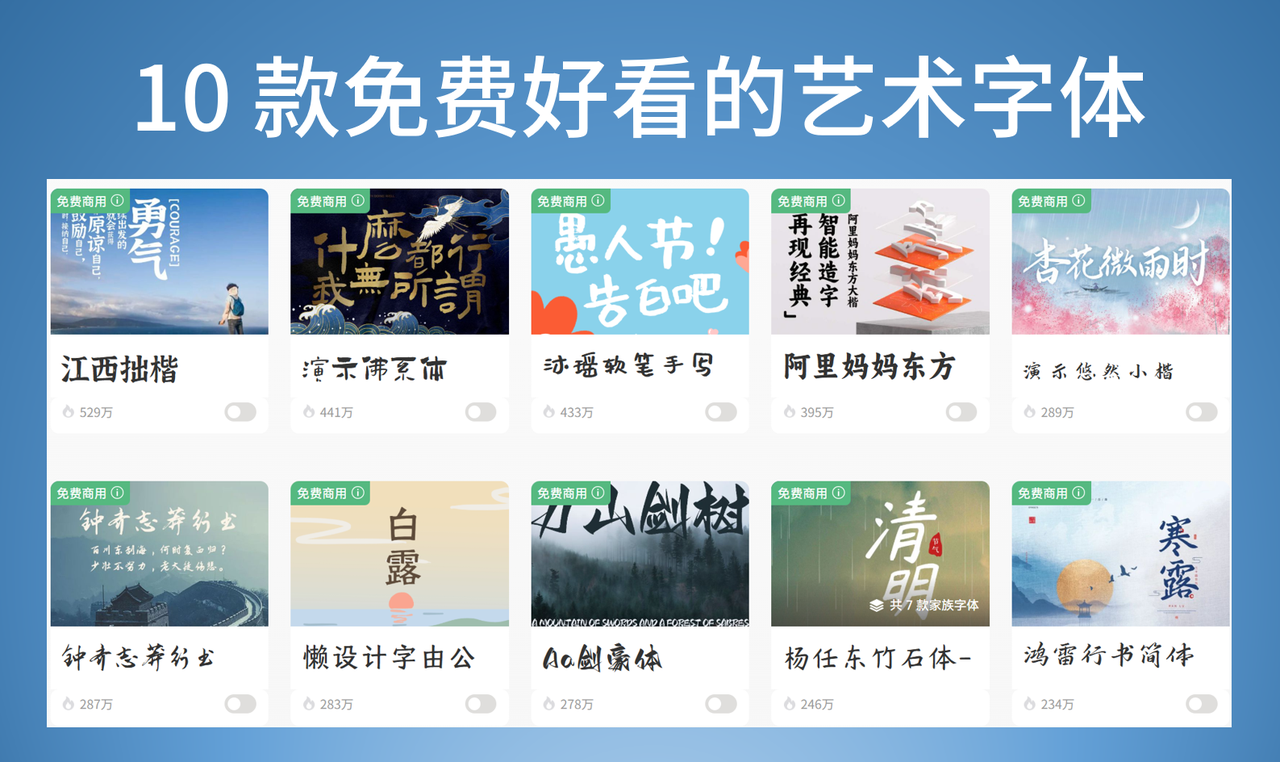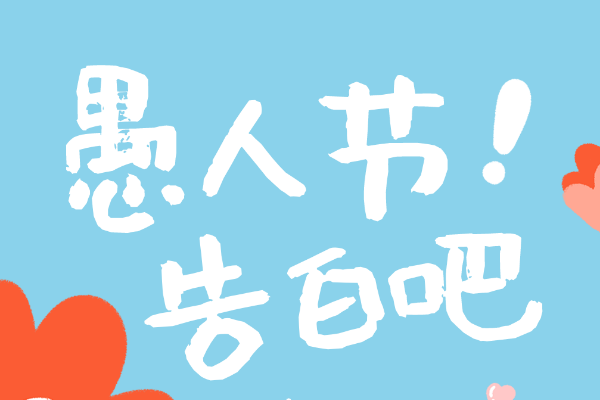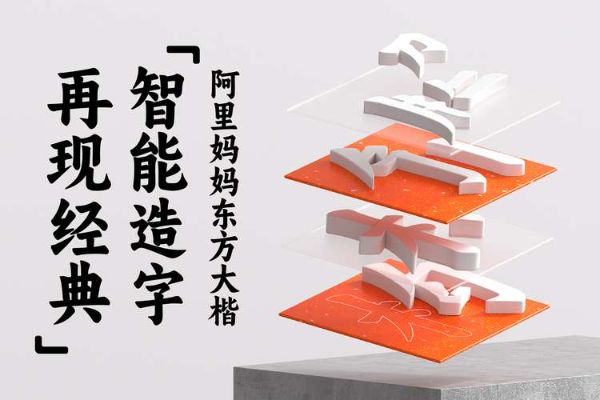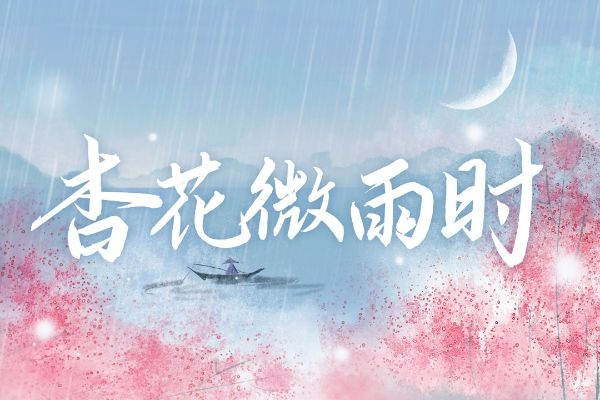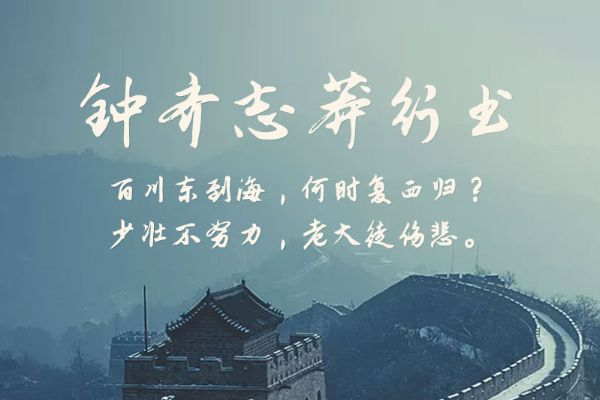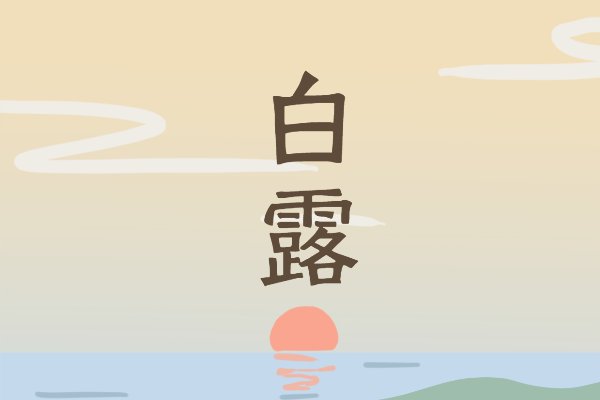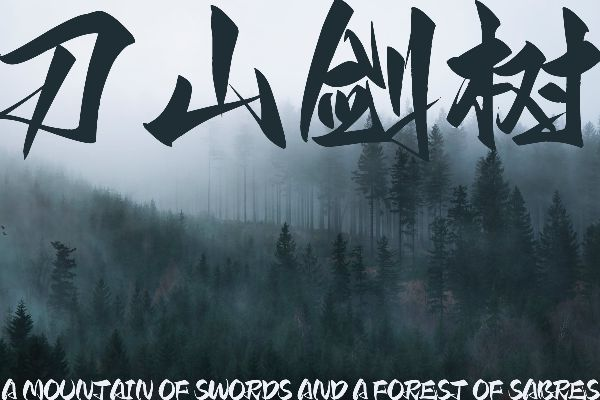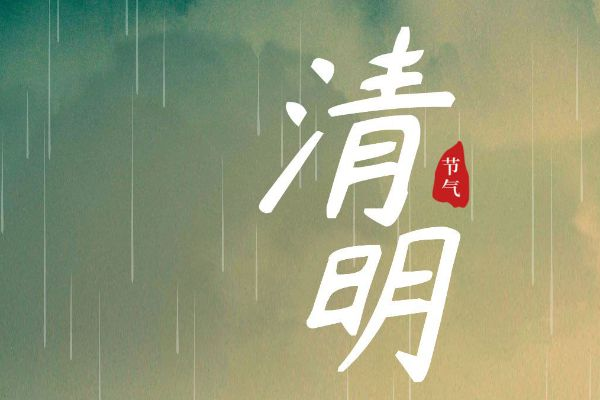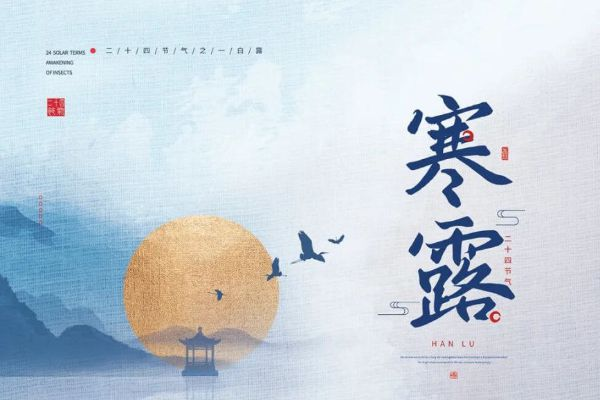
艺术字体大全,10 款免费好看的艺术字体分享
艺术字体是设计师和文案工作者们常用的一种字体类型。无论是海报设计、品牌LOGO,还是各种创意排版,艺术字体总能带来独特的视觉冲击力。本文会重点给大家分享 10 款免费好看的艺术字体,帮助大家在设计海报和其它作品时,更加有艺术感。
一、什么样的字体才算艺术字体
艺术字体不仅仅注重字形的清晰传达,更关注字体的视觉美感和表现力的字体。它们往往具有较强的个性化和装饰性,可以通过曲线、笔触、色彩甚至三维效果来表达独特的艺术风格。艺术字体不像常规的宋体、黑体那样严谨规范,而是更自由、更具创造性,适合用来表达情感和氛围。
二、艺术字体的特点
1. 个性鲜明
艺术字体形态多样,可能是优雅的曲线,也可能是粗犷的笔触,甚至结合了多种设计元素。所以具有强烈的个性特点,能够迅速吸引观众的注意力。
1. 装饰性强
相比标准字体,艺术字体更注重视觉装饰效果,往往带有复杂的线条、阴影、渐变和花纹,使字体本身成为一种艺术品。
1. 灵活多变
艺术字体的设计非常灵活,可以根据不同的主题和情境进行调整和创新,满足不同的设计需求。
1. 易于传递情感
艺术字体通过形态和设计传达特定的情绪和氛围,比如浪漫、复古、现代、街头风等,增强视觉沟通的效果。
三、艺术字体的使用场景
1. 品牌标识设计
作为品牌的标识,当然需要更具有艺术感,更容易被用户记住,例如时尚品牌、餐饮品牌常用手写风格或复古风艺术字体,增强辨识度。
1. 海报
尤其在影视宣传海报中,艺术字体非常受欢迎,尤其是电影海报、演唱会宣传等,需要强烈视觉冲击和情感表达的场合。
1. 书籍封面与杂志排版
为了吸引读者注意,书籍或杂志封面常用艺术字体来突出主题,增强视觉美感。
1. 网页设计和社交媒体
在网页标题、Banner和社交媒体配图中,艺术字体可以提升整体设计感,吸引更多点击和关注。
1. 包装设计
食品、化妆品等产品包装中,艺术字体能够传达产品的独特风格和品质感。
四、10 款免费好看的艺术字体
1. 江西拙楷
江西拙楷是一款充满传统韵味的楷书字体,这款字体在设计上强调笔画的厚重感和结构的严谨性,让人感受到中华汉字的独特魅力。
字体特点:
• 字体的笔画粗细适中,书写感厚实,笔力遒劲,给人一种稳重坚实的感觉。
• 字形布局方正,结构平衡,每个字的重心都非常稳定,易于识别和阅读。
• 在规整中透露出一种自然的拙朴感,更显真诚和艺术性。
1. 演示佛系体
演示佛系体是一款充满禅意与宁静的手写风格字体,这款字体摒弃了锋利的棱角,呈现出一种圆润、随性的艺术气息。
字体特点:
• 字形线条柔和,转折圆滑,避免了生硬的笔锋,给人舒适的视觉体验。
• 带有手写体的随意感,散发出一种无拘无束的轻松感觉。
• 如同日常手写的文字一样,具有亲切感,拉近了与读者的距离。
1. 沐瑶软笔手写体
沐瑶软笔手写体是一款融合了软笔书法独特韵味与现代手写风格亲切感的字体。它以细腻而富有弹性的笔触,展现出一种既优雅又充满活力的书写姿态。
字体特点:
• 字体的笔画粗细变化自然,带有软笔书写特有的柔韧感和流动性。
• 保留了手写字体的自然痕迹和连笔特征,显得亲切且富有艺术气息。
1. 阿里妈妈东方大楷
阿里妈妈东方大楷是阿里巴巴旗下推出的一款现代化楷书字体,这款字体旨在提供一款既有文化底蕴,又能适应数字时代多场景应用的高质量中文楷体。
字体特点:
• 笔画粗壮有力,字形结构开阔,整体视觉效果大气、宏伟。
• 在保留楷书端正特点的同时,笔画处理更加简洁有力,富有现代设计感。
• 清晰的笔画和稳定的结构,确保了在各种尺寸和背景下都能保持优秀的辨识度。
1. 演示悠然小楷
演示悠然小楷是一款精致而富有韵味的小楷字体,它以其细腻的笔触和雅致的字形,展现出一种宁静、从容的书写风貌。
字体特点:
• 整体字形设计紧凑而雅致,细节处理精细。
• 线条纤细而富有力量,书写感优美,视觉感受非常流畅。
• 字形结构清晰,笔画分明,在小字号下依然保持良好的可读性。
1. 钟齐志莽行书
钟齐志莽行书是一款充满艺术激情和个性化风格的行书字体。
字体特点:
• 每个字的结构和笔画处理都富有个性,打破了传统楷书的规整,更显灵动。
• 整体风格富有艺术感染力,能有效传达情感和作者的个性。
1. 懒设计字由公益体
懒设计字由公益体是一款由“懒设计”平台联合“字由”推出的公益性字体。它以现代、简洁、实用的设计理念为核心,旨在为广大设计师和非专业用户提供一款免费且高质量的字体。
字体特点:
• 字形设计时尚简约,笔画清晰流畅,符合现代审美趋势。
• 字形结构稳定,笔画粗细适中,确保了在不同尺寸下的清晰辨识。
• 作为公益字体,其最大的特点是支持免费商业用途,极大地降低了设计师的成本。
1. Aa剑豪体
Aa剑豪体是一款充满武侠气息和力量感的创意字体。它将中国传统武术中“剑”的凌厉与“豪”的洒脱融入字体设计。
字体特点:
• 字体的笔画如同剑锋般锐利,充满力量感,切割感强烈。
• 整体字形和笔画处理都带有鲜明的武侠元素。
• 辨识度极高,能够瞬间吸引目光并留下深刻印象。
1. 杨任东竹石体
杨任东竹石体是一款以自然元素“竹”与“石”为灵感的手写风格字体。字体笔触自然,如同竹叶随风摇曳,又如顽石般沉稳。
字体特点:
• 保留了手写字体的自然不羁,笔触生动,富有个性。
• 整体气质透露出一种清新、淡雅、回归自然的感觉。
1. 鸿雷行书简体
鸿雷行书简体是一款流畅而富有韵律感的行书字体,它在传统行书的基础上进行了现代化简化处理,使其更易于在数字环境中应用。这款字体笔势连贯,结构舒展,兼具书法的艺术性和现代的实用性。
字体特点:
• 字体的笔画之间衔接自然,行云流水。
• 字形开放,布局合理。
• 简化了过于复杂的笔画,提高了可读性。
• 仿佛能够看到书写者笔墨挥洒的痕迹,富有生命力。